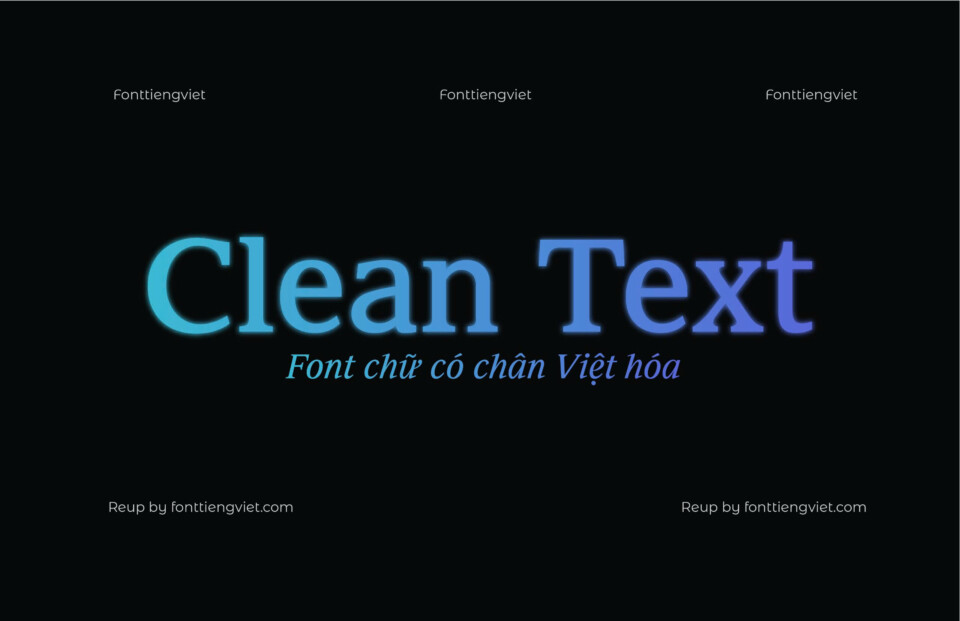
Giới thiệu bộ Font Việt hóa ClearTextMedium ( 2 file )
Trong thế giới thiết kế đồ họa hiện đại, việc lựa chọn Font Chữ phù hợp đóng vai trò quyết định đến hiệu quả truyền tải thông điệp. Bộ Font Việt hóa ClearTextMedium ( 2 file ) là một giải pháp hoàn hảo cho những ai đang tìm kiếm sự đơn giản nhưng không kém phần chuyên nghiệp. Với cấu trúc đường nét rõ ràng và độ dày vừa phải, bộ font này giúp người xem dễ dàng tiếp nhận nội dung mà không gây mỏi mắt. Đây là bộ phông chữ lý tưởng dành cho các dự án liên quan đến giáo dục, bài giảng điện tử và trình bày văn bản hành chính.
Đặc điểm nổi bật của Font Việt hóa ClearTextMedium ( 2 file )
Thiết kế tối ưu cho hiển thị
Bộ font này bao gồm hai tệp tin riêng biệt, hỗ trợ tối đa các ký tự tiếng Việt có dấu một cách chuẩn xác. Điểm mạnh lớn nhất của ClearTextMedium chính là sự cân bằng giữa các khoảng hở, giúp chữ viết luôn sắc nét trên cả màn hình máy tính lẫn bản in. Các em học sinh và thầy cô giáo có thể sử dụng font này để soạn thảo giáo án hoặc làm slide thuyết trình nhằm tăng tính thẩm mỹ và sự tập trung.
Tính ứng dụng đa dạng trong nhà trường
Không chỉ dừng lại ở các văn bản thông thường, bộ font còn rất được ưa chuộng trong việc thiết kế poster cổ động, sơ đồ tư duy hay các bảng tin nội bộ. Sự hiện diện của 2 file giúp người dùng linh hoạt hơn trong việc phối hợp các kiểu định dạng khác nhau.